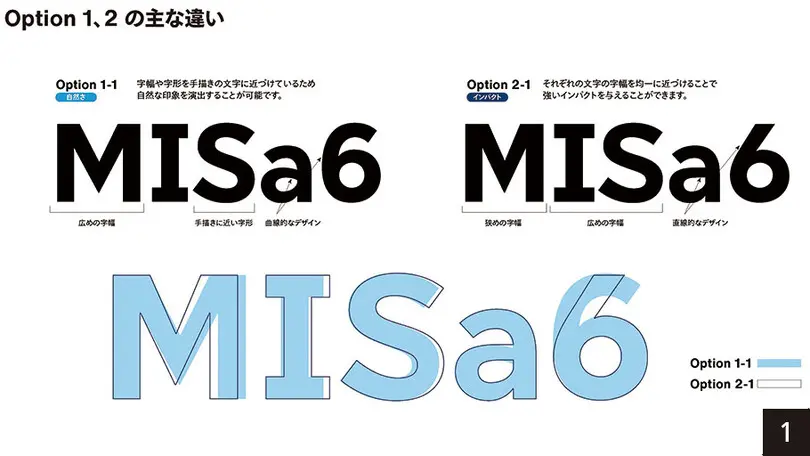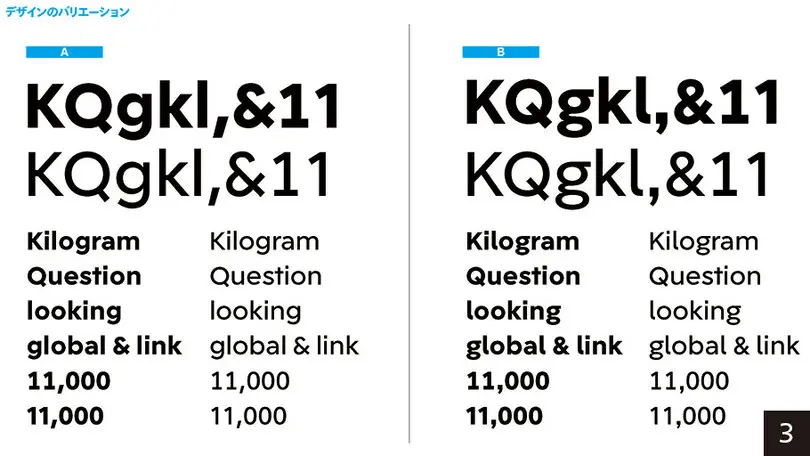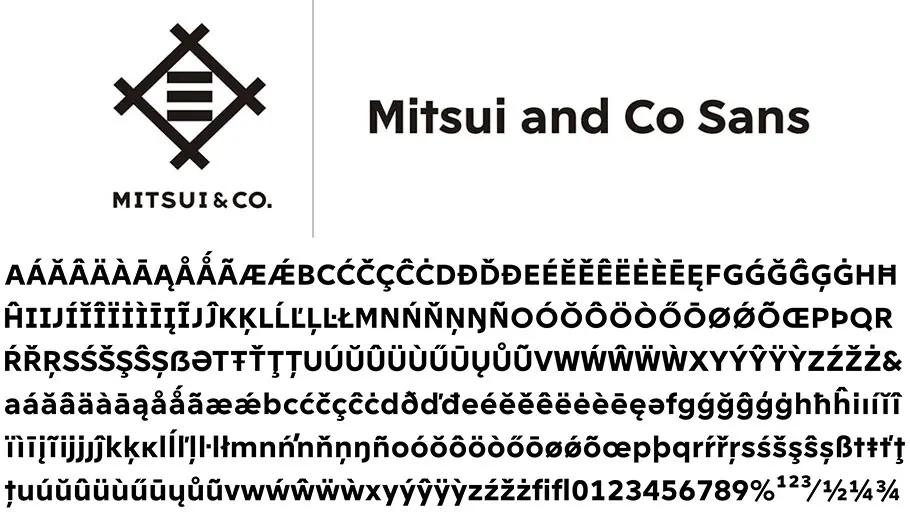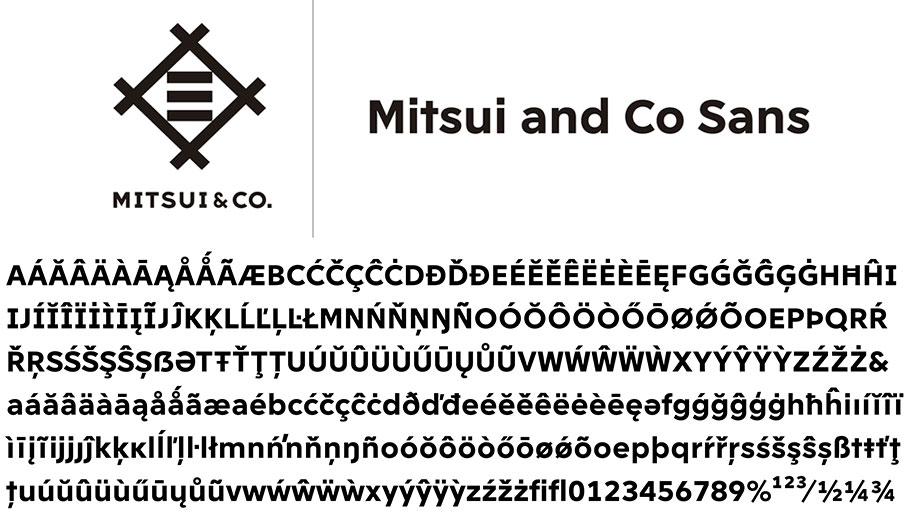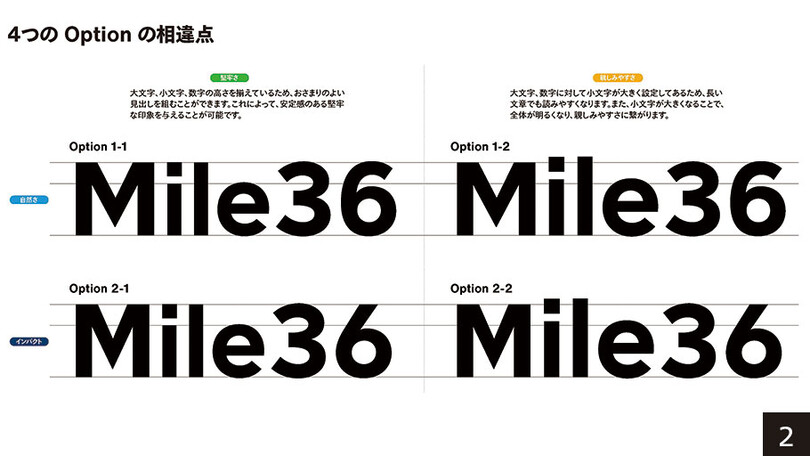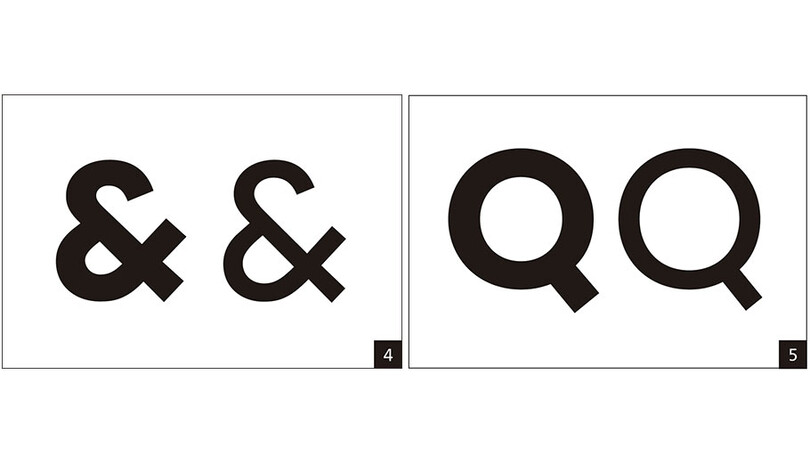
ロゴが表現する企業の姿をカスタムフォントに
「 最近の流行を意識しつつも、企業ブランドの本質がロゴに表現されています。文字デザインがぶれることなく、基本に立ち戻ることができる井桁三のロゴの存在は非常に大きいです。 」
クリエイティブタイプディレクター小林章
多言語対応をした欧文カスタムフォントを制作 ロゴの「近代的で明るい表情」を文字からも発信
三井物産株式会社は、 2014年から企業理念をグローバルに浸透させる三井物産ブランド・プロジェクトに取り組んでいます。
トータル・プロデューサーとして、クリエイティブディレクター佐藤可士和氏を起用、300年以上の歴史を持つ三井の店章(丸に井桁三)を受け継ぐ三井物産のロゴを刷新し、より現代的でシャープなプロポーションとした現在のロゴが誕生しました。またロゴにおける社名表記を「MITSUI & CO.」に統一し、世界中に共通した三井物産の理念を発信しています。
Monotypeは、このロゴの印象からかけ離れず、しかも文章を組んで読みやすい欧文カスタムフォントの制作を手掛けました。 クリエイティブスタジオSAMURAIの佐藤可士和氏とMonotypeのクリエイティブタイプディレクターの小林章は、過去10年にわたりブランディングと欧文カスタムフォント制作に関わる仕事を重ねてきました。
佐藤可士和氏は、書体について次のように語ります。「人は大抵の場合、ロゴマークを見ているとき、企業メッセージが込められたイメージと意識して目に入れます。でも、例えばウェブサイトに書かれている情報を読むときはどうでしょうか。文字の形を意識しながら文章を読むということはほとんどないと思います。しかし、文章を読んでいるときでも、文字を通して企業とのコミュニケーションは行われているのです。その文字に一貫性がなかったとしたら、あるいは、どこにでもあるような個性のない文字が使われていたら、それは貴重なコミュニケーションの機会を失っていることとなります。企業コミュニケーションのツールとして重要なフォントのデザインを見直し、ブランドコミュニケーションの効率を上げていく必要があります」。
The Challenge(チャレンジ):
世界中でビジネス展開する上で、三井物産ではウェブサイト、会社案内、プレゼンテーション、名刺などさまざまな状況において欧文書体で表記されたコミュニケーションが求められます。三井物産のロゴがもつブランドメッセージを欧文書体からも同じように発信できるようにと、佐藤可士和氏とMonotypeのスタジオチームが協力し、欧文カスタムフォントの開発が始まりました。
Solution(ソリューション):
書体は個性を持っています。カスタマイズデザインを提案する際は、書体から受ける印象はキーワードを通して具体化し、開発の方向性を確認しあう作業から入ります。ここで重要となるのは、ロゴが表現する「近代的で明るい表情」を、文字に表していくことです。文字の幅や曲線、エックスハイト(小文字の高さ)を調節することで、文字の個性の引き出し方が異なってきます(図1)。
Monotypeカスタムフォント例
Option1)より普遍的で自然な印象。普段読み慣れている文字のバランスに近いため、読みやすさの点で有利
Option 2)現行のロゴから少しアレンジ。読み慣れた欧文のリズムとはちょっと違う、あえて引っ掛かりを持たせたインパクト重視のデザイン また、文字一つ一つの印象に加えて、文章という文字の塊になった時の印象も重要です。デザインチームは文章を読む人がどんなブランド体験をするのかを具体的に提案します。 ここでは、親しみやすさの中にもロゴのもつインパクト感を持ち合わせる Option 2-2が選ばれました(図2)。
大文字、数字に対して小文字が大きく設定してあるため、長い文章でも読みやすくなります。また、全体が明るくなり、親しみやすさに繋がります。さらに進んだ段階のサンプルでは、アルファベット、数字、&(アンパーサンド)などの記号を制作するための提案が出されました。ロゴのデザインがもつメッセージ性を踏襲しつつ、可読性を保つ文字のバリエーションを追求していきます。
小文字l(エル)のバリエーションについても丁寧な意識のすり合わせが行われました。バリエーションAのほうは縦棒のみ、バリエーションBのほうはフックのついたデザインが提示されましたが、ここで選ばれたのはバリエーションAでした(図3)。
「このフックのついたl(エル)は、トレンドとしてだんだん増えていることから試作に入れてみました。今回の書体では大文字 I(アイ)の上下にセリフがあるために混同される恐れは少ないということで、フックのついていないl(エル)が採用されました。最近の流行を意識しつつも、企業ブランドの本質がロゴに表現されています。文字デザインがぶれることなく、基本に立ち戻ることができる井桁三のロゴの存在は非常に大きいです。」と、クリエイティブ・タイプディレクターの小林章は述べます。
ロゴマークに使用されている&(アンパーサンド)の独自性も、バリエーション選考基準の参考となっています。例えば、大文字のQは、テール(尻尾)がOの部分を突き抜けているスタイルと突き抜けていないスタイルのバリエーションが提示されました。ここでもロゴにならい近代的な見え方のQが選ばれましたが、打ち合わせ中にご担当者さまから、視認性についてのご質問をいただきました。
「欧文でよく使われるFrutiger, Avenirなどの書体でも、突き抜けていないQが使用されていますので、実際に世にでている標識やパッケージなどの使用例をお見せし、納得をしていただきながら書体デザインを進めました。」とシニア・タイプデザイナーの土井遼太は述べます。
Outcome(結果):
完成したオリジナルの欧文書体はMitsui and Co Sansと名付けられました。近代的で明るい表情をもち、Regular、Italic、Bold、Bold Italicの4スタイルから構成されています。これにより、ウェブサイト、プレゼンテーション、名刺の文字組みに必要な実用的な書体が揃いました。イタリック体の使い方についてはいくつかルールがあり、語句の強調、外来語の表記、書籍や演劇または映画のタイトル、音楽や芸術作品名、船舶や機関車につけられた名前などを示すのに使われます。文字自体が表現するという意味では、世界とコミュニケーションする際に重要不可欠な要素です。
「三井物産では、現場の社員一人ひとりがブランドの体現者として顧客に、社会に、パートナーに、『ブランドのあるべき姿』を発信すると掲げています。彼らが日常的に触れている文字を通して、社員がブランド体験し、その体験をさらに社内そして社会のみなさまに発信できることはすばらしいことです。」と三井物産、広報部コーポレートブランディング室長の津田圭吾氏は述べます。
Mitsui and Co Sans が加わったことで視覚的表現が豊かになった三井物産ブランドは、これからも全世界に向けて発信し続けられるでしょう。